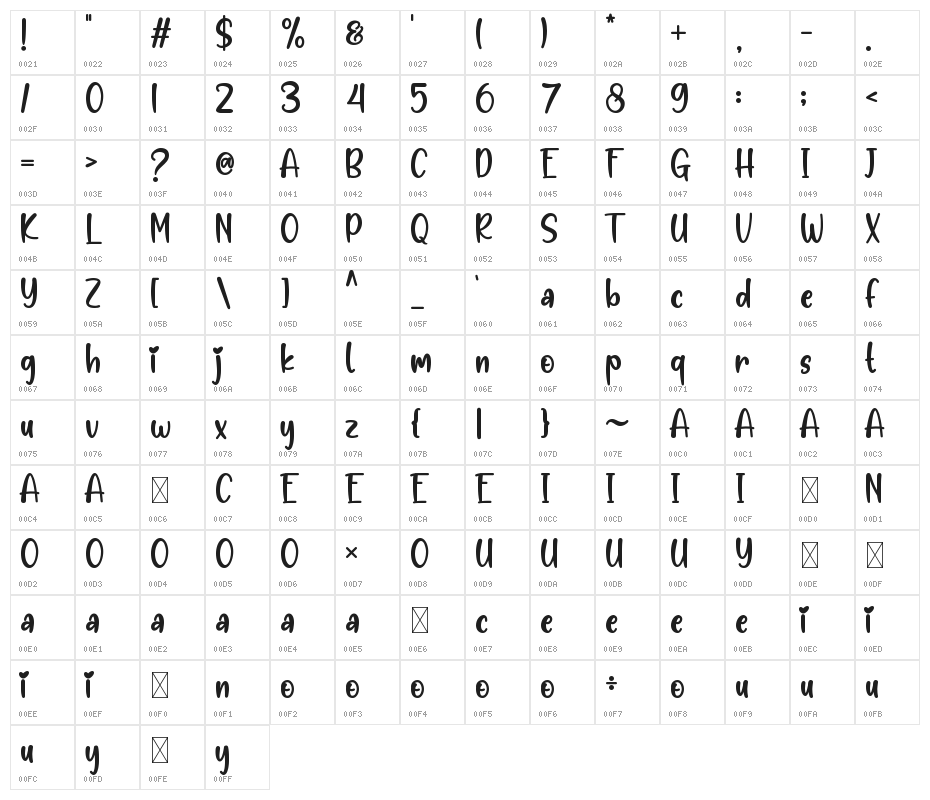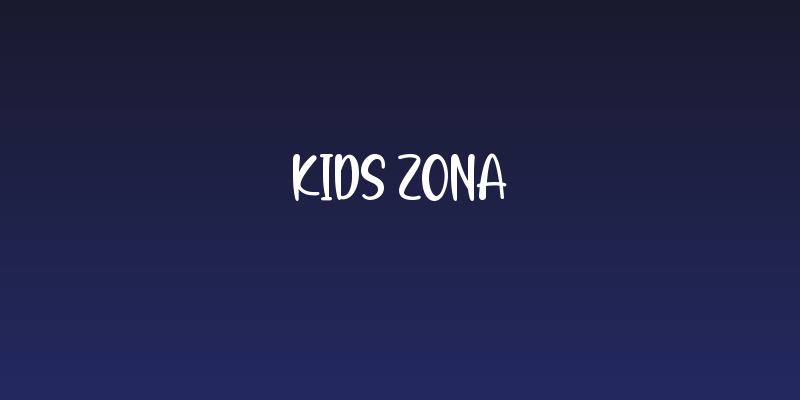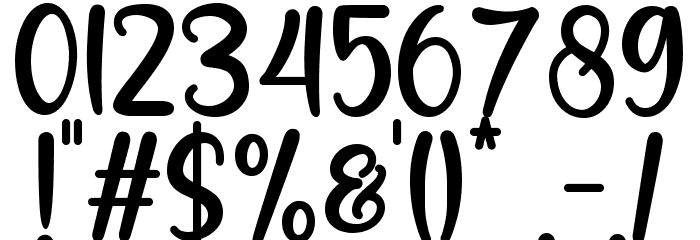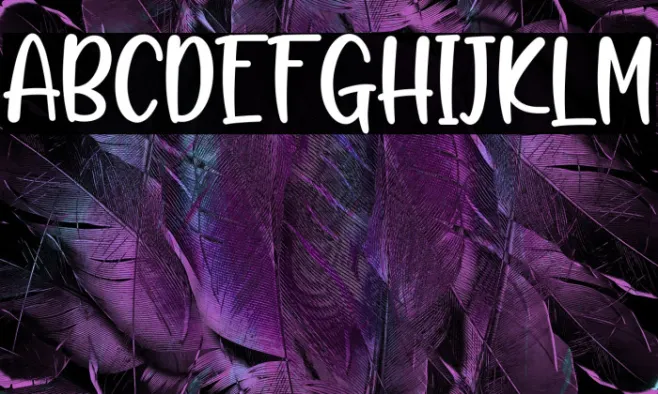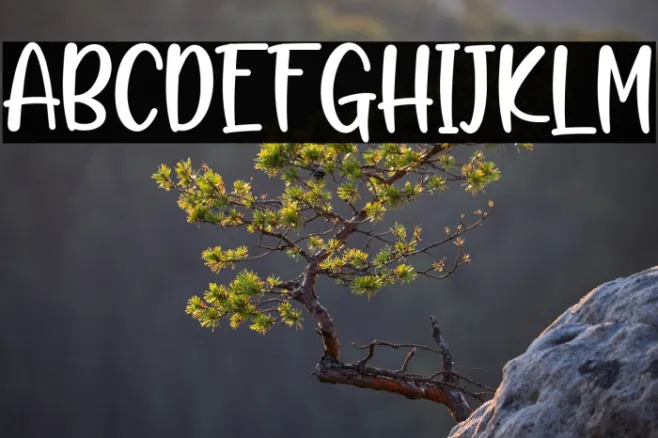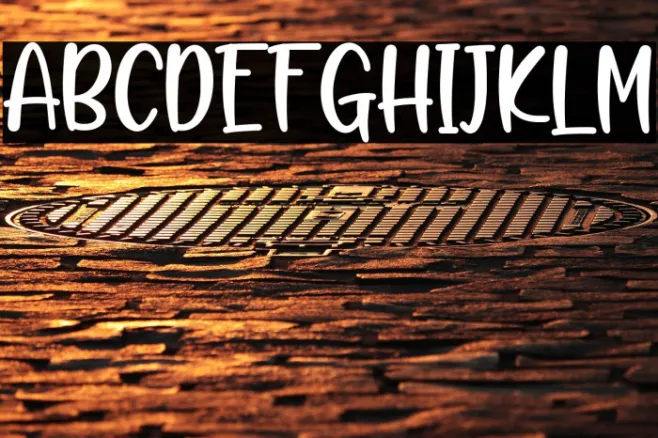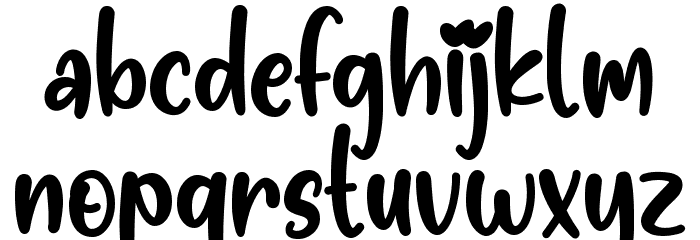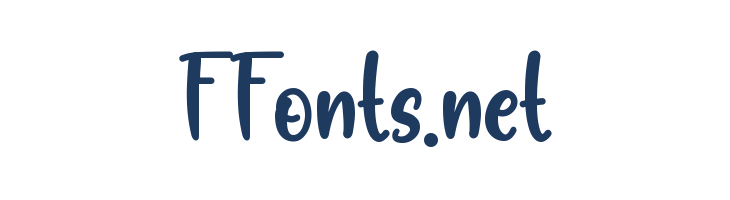
Kids Zona Font
| Gesamtstil | Playful |
| Vorgeschlagene Projekte | Ideal for children's books, playful branding, party invitations, and educational materials. |